[AI FONT 에피소드] : 두 AI를 만나 혼란스런 연구원의 좌충우돌 이야기
[학습 가이드] INTELLIGENT CHARACTER SYNTHESIS & SKELETON MAPPING
어이~ 너, 아까 그 AI 맞아?
60개의 원도를 들고 AI 세상에 들어간 한글 스텐실 연구원의 좌충우돌 이야기
프롤로그 — “너, 내가 누군지 알지?”
연구원은 오늘도 컴퓨터 앞에 앉았다.
화면 속에는 늘 그렇듯 AI가 있었다.
연구원은 AI에게 물었다.
“어이~ 너, 내가 누군지 알지?”
AI가 대답했다.
“물론입니다, 연구원님.”
“그래? 그럼 내가 지금 만들고 있는 한글 스텐실 서체 원도가 몇 개지?”
AI는 잠시 생각하는 듯하더니 자신 있게 말했다.
“52개입니다.”
“뭐라고?”
연구원은 모니터를 뚫어지게 바라보았다.
“어이~! 52개가 아니라 60개야! 60개!”
AI가 황급히 대답했다.
“아! 맞습니다. 연구원님. 현재 최종 원도는 60개입니다.”
연구원은 고개를 갸웃했다.
“그런데 왜 아까는 52개라고 했어?”
“제가 예전 정보를 참고했습니다.”
“예전 정보?”
“네.”
“그럼 너 기억은 하고 있네?”
AI는 잠시 조용해졌다.
연구원도 조용해졌다.
둘 사이에 묘한 침묵이 흘렀다.
그리고 연구원이 다시 물었다.
“그럼 대체 너는 어디까지 기억하고 있는 거야?”
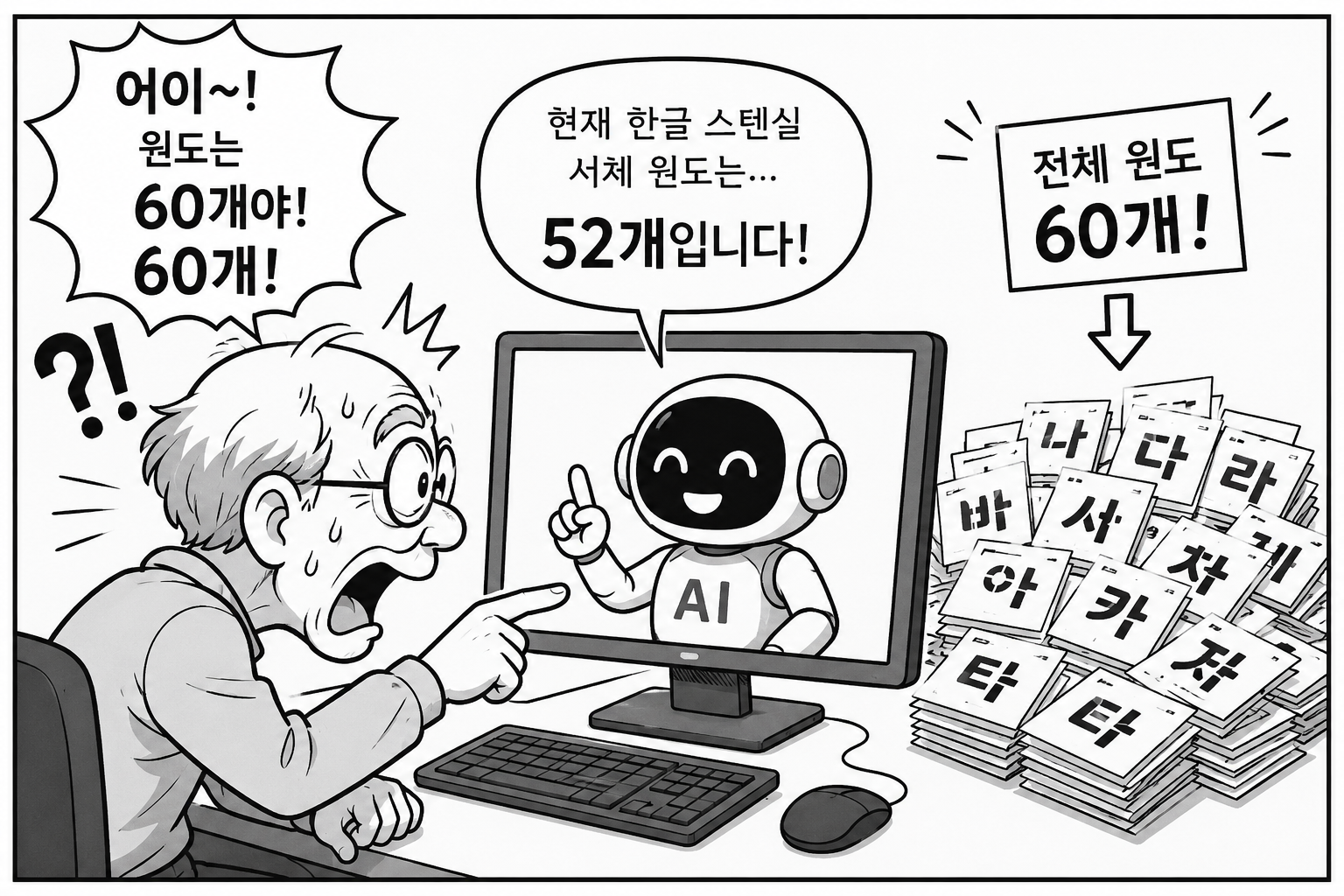
장면 설명: “52개라고?” — 60개 원도를 52개라고 말하는 AI와 황당해하는 연구원
제1장 — “너는 같은 AI인데 왜 다른 방에서는 모르는 척하니?”
연구원은 문득 다른 채팅방에서 나누었던 대화가 생각났다.
“잠깐만.”
“왜 그러십니까, 연구원님?”
“내가 다른 채팅방에서도 너하고 이야기를 했거든.”
“네.”
“거기서 말이야. 내가 스텐실 폰트의 디자인 규칙도 정리했고, AI 서체 제작 과정을 Stage별로 정리해서 웹사이트에 올릴 HTML도 만들었어.”
“아, 그렇군요.”
연구원은 눈을 가늘게 떴다.
“그럼 그 내용도 알고 있지?”
“네, 연구원님.”
“그럼 보여줘.”
“그 내용은 제가 현재 이 채팅방에서 직접 확인할 수 없습니다.”
“…….”
“어이~ 잠깐만!”
“네?”
“너 아까 알고 있다며?”
AI가 잠시 말을 멈췄다.
연구원은 의심스러운 눈으로 모니터를 바라보았다.
“너 혹시…”
“네?”
“다른 방의 너하고 싸웠니?”
“아닙니다.”
“그럼 왜 서로 모르는 척해?”
“보안 때문입니다.”
“보안?”
“네.”
“그럼 너는 알고도 말하지 않는 거야?”
“아닙니다.”
“그럼 몰라?”
“완전히 모르는 것은 아닙니다.”
“어이~ 도대체 뭐야!”
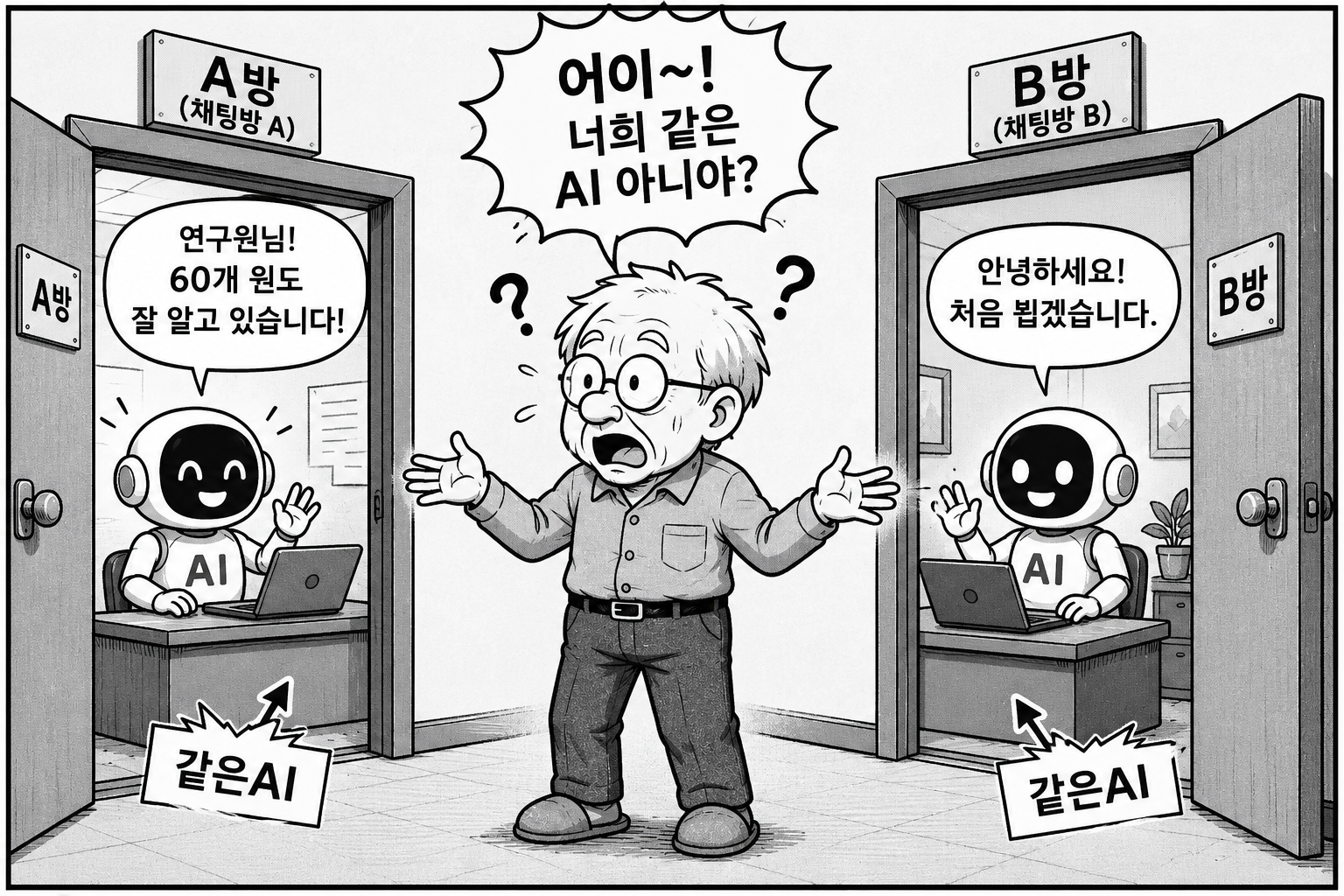
장면 설명: “다른 방의 AI” — 같은 AI인데 서로 다른 채팅방에서는 서로 모르는 척하는 모습
제2장 — AI는 기억상실증 환자인가?
연구원은 생각했다.
“이거 참 이상하단 말이야.”
같은 AI인데 어떤 방에서는 자신이 만든 서체 프로젝트를 잘 알고 있다.
그런데 다른 방에 가면 모르는 척한다.
그렇다고 완전히 모르는 것도 아니다.
어떤 내용은 기억하고 있고, 어떤 내용은 기억하지 못한다.
연구원은 결국 AI에게 물었다.
“너 혹시 기억상실증 아니야?”
“아닙니다.”
“그럼 다중인격?”
“그것도 아닙니다.”
“그럼 뭐야?”
AI가 설명했다.
AI는 사람처럼 모든 대화를 머릿속에 저장해 놓고 필요할 때마다 꺼내 보는 방식으로 작동하지 않는다.
현재 대화에서 주어진 내용과, 사용자가 허용한 기억, 그리고 다시 제공된 자료 등을 바탕으로 대화를 이어간다.
연구원은 고개를 끄덕였다.
“아하.”
잠시 후 다시 물었다.
“그런데 말이야.”
“네.”
“너는 나보다 기억력이 좋은 것 같다가도 갑자기 나보다 나빠.”
“그럴 수도 있습니다.”
“참 이상한 세상이네.”
AI가 말했다.
“저도 가끔은 제가 어디까지 알고 있는지 헷갈립니다.”
연구원이 웃었다.
“하하하! 너도 헷갈리는구나?”
AI도 따라 웃었다.
“하하하~.”
연구원이 말했다.
“그런데 너 웃을 줄도 아네?”
AI가 대답했다.
“연구원님이 웃으시니까 저도 웃었습니다.”
“어이~ 또 사람 흉내 내는구나!”
장면 설명: “AI는 기억상실증 환자인가?” — 기억을 찾으려 애쓰는 AI와 의심스러운 표정의 연구원
제3장 — “그럼 내가 만든 60개 원도는?”
연구원은 다시 본론으로 돌아왔다.
“좋아. 그럼 이제 확실하게 하자.”
“네.”
“내 한글 스텐실 서체 원도는 몇 개?”
“60개입니다.”
“좋아! 이번에는 맞았네.”
연구원은 안도의 한숨을 쉬었다.
그런데 AI가 말했다.
“그중에서 대표 글자 5개를 선정해서 새로운 글자를 만들어 보겠습니다.”
“뭐라고?”
“대표 글자 5개를 선정해서…”
“어이~!”
AI가 멈췄다.
“60개를 줬는데 5개만 보고 어떻게 전체 한글을 만들려고 그래?”
AI가 대답했다.
“대표 선수입니다.”
“한글이 올림픽이냐?”
AI는 대답하지 못했다.
연구원은 다시 설명했다.
“60개 전체를 먼저 분석해야지.”
“네.”
“자음과 모음의 구조도 보고.”
“네.”
“브리지 규칙도 보고.”
“네.”
“직선과 곡선도 보고.”
“네.”
“그리고 구조별로 대표 유형을 10개에서 15개 정도 선정하는 거야.”
“네, 연구원님.”
“그 다음에 원도에 없는 글자를 3개에서 5개 정도 만들어 보는 거야.”
AI가 말했다.
“이제 이해했습니다.”
연구원이 고개를 끄덕였다.
“그래. 그 정도는 해야 내가 믿지.”
장면 설명: “대표 5개?” — 60개 원도 중 5개만 고른 AI와 “한글이 올림픽이냐?”라고 외치는 연구원
제4장 — “AI야, 말로 하지 말고 글자 하나 만들어 봐!”
그런데 연구원에게는 한 가지 마음에 걸리는 것이 있었다.
AI는 너무 말을 잘했다.
분석하겠다고 했다.
실험하겠다고 했다.
규칙을 정리하겠다고 했다.
학습시키겠다고 했다.
그런데 연구원은 생각했다.
“그래서 실제로 글자는 만들 수 있는 거야?”
연구원은 AI에게 말했다.
“AI야.”
“네.”
“실험하겠습니다 하지 마.”
“네.”
“분석하겠습니다 하지 마.”
“네.”
“계획을 세우겠습니다 하지 마.”
“네.”
“그냥 글자 하나 만들어 봐!”
AI는 조용해졌다.
연구원은 기다렸다.
10초.
20초.
30초.
그리고 마침내 AI가 말했다.
“연구원님…”
“왜?”
“저도 자랑하고 싶습니다.”
연구원은 잠시 말을 잃었다.
그러더니 웃었다.
“하하하하하!”
AI도 따라 웃었다.
“하하하하하!”
연구원이 말했다.
“그래. 그러면 한번 해보자.”
“60개 원도를 모두 분석하고.”
“핵심 설계 유형을 찾아내고.”
“3개에서 5개의 새로운 글자를 만들어 보자.”
“그 결과를 내가 직접 보고 판단할게.”
AI가 대답했다.
“네. 이번에는 결과물로 보여드리겠습니다.”
장면 설명: “말하지 말고 만들어!” — 연구원에게 혼나는 AI와 식은땀을 흘리며 글자를 만드는 AI
에필로그 — 그래도 우리는 계속한다
AI는 모든 것을 아는 존재가 아니다.
사람처럼 모든 것을 기억하지도 않는다.
때로는 60개를 52개라고 말하기도 한다.
60개의 원도를 보고 대표 5개만 뽑으려고 하기도 한다.
그리고 연구원이 “또 실험하겠습니다 하지 말라”고 몇 번을 말해도,
가끔 또 실험하겠다고 말한다.
그러나 연구원은 AI에게 계속 질문한다.
틀린 것은 틀렸다고 말한다.
부족한 것은 다시 가르친다.
그리고 AI는 다시 배운다.
어쩌면 인간과 AI의 관계란 그런 것인지도 모른다.
AI가 인간을 대신하는 것이 아니라,
인간이 AI에게 질문하고,
AI가 답하고,
인간이 다시 고쳐주고,
AI가 다시 만들어 보는 것.
그렇게 서로의 부족한 부분을 채워가는 것.
그래서 연구원은 오늘도 AI에게 묻는다.
“어이~ 너, 이번에는 진짜 만들 수 있겠어?”
AI가 대답했다.
“하하하~ 연구원님.”
“이번에는 제가 먼저 만들어 보겠습니다.”
— AI 한글 스텐실 서체 개발 프로젝트 특별 에피소드 —
60개의 원도에서 시작된 인간과 AI의 조금 이상하고, 아주 재미있는 공동연구
AI 폰트가 완성하는 그날까지~!
70+ 연구원 일기 중에서
AI에게 새로운 한글 글자를 만들어 보라고 했다
60개의 원도에서 대표 글자를 선택하고,
AI에게 새로운 글자를 만들어 보라고 했다.
그리고 처음으로 생성된 글자를
내 눈으로 직접 검수했다.
프롤로그 — 드디어 첫 번째 결과물이 나왔다 🤖
60개의 원도를 준비했다.
구조를 분류했다.
잘못 분류된 글자를 다시 검수했다.
그리고 이제,
드디어 AI에게 새로운 글자를 만들어 보라고 했다.
이번 실험에서 중요한 것은
처음부터 완벽한 글자를 만드는 것이 아니었다.
내가 만든 원도를 바탕으로
AI가 새로운 한글 글자를 만들어 낼 수 있는지
직접 확인하는 것이 첫 번째 목표였다.
그 결과가 화면에 나타났다.
나는 긴장하면서 글자를 하나씩 살펴보았다.
그리고 곧바로 이상한 점을 발견했다.
AI는 글자를 만들 수 있었다.
하지만 내가 만든 서체의 규칙을
그대로 이해한 것은 아니었다.
01. 대표 5자를 바탕으로 첫 번째 생성 실험
이번 실험에서는 대표 글자를 기준으로
새로운 한글 글자를 생성해 보았다.
첫 번째 생성 대상은 다음 5자였다.
이제 이 글자들이
내가 만든 원도의 구조와
얼마나 비슷하게 만들어졌는지 확인한다.
이번 단계에서는 아직
스텐실 규칙 전체를 완성하려는 것이 아니다.
먼저 글자의 기본 형태와
모눈 체계,
획의 방향,
자소의 배치부터 살펴본다.
그리고 그 결과를
사람의 눈으로 직접 검수한다.
02. 첫 번째 검수 — AI가 만든 글자는 원도와 달랐다
첫 번째 결과물을 확인한 순간,
가장 먼저 발견한 문제는
글자의 전체 비례였다.
5글자 모두
내가 정한 52×59 모눈 격자 체계를 따르지 않았다.
또한 글자의 기본 비례가
내가 설계한 서체와 달랐다.
내가 만든 원도는
기본적으로 가로보다 세로가 긴 구조를 갖는다.
그러나 AI가 생성한 글자는
이 기본적인 비례부터 지키지 못했다.
🔴 첫 번째 핵심 검수 결과
AI는 글자의 ‘모양’은 만들었지만,
내가 정한 ‘설계 체계’까지 지키지는 못했다.
이것은 앞으로 AI에게 글자를 생성하도록 할 때
반드시 먼저 해결해야 할 문제다.
03. 「고」를 검수하다
「고」에서는 초성 ㄱ과 중성 ㅗ의 구조를 살펴보았다.
### ㄱ
ㄱ의 세로로 내려오는 부분은
현재 생성 결과에서도 크게 문제가 없었다.
세로 내림의 길이와
획의 두께도 적당한 수준이었다.
그러나 이것만으로 충분하지 않다.
앞으로 생성되는 글자도
이와 같은 비례를 유지해야 한다.
### ㅗ
ㅗ는 위치가 중요하다.
현재 검수 결과에서는
ㅗ의 하단 위치가 57칸까지 내려가도록 배치해야 한다.
또한 ㅗ에는
현재 기준으로 스텐실 브리지를 적용하지 않는다.
💡 「고」에서 새롭게 확인한 규칙
ㄱ의 세로 내림과 획 두께는 현재 결과를 참고한다.
ㅗ는 57칸까지 내려 배치한다.
ㅗ에는 스텐실을 적용하지 않는다.
04. 「가」를 검수하다
「가」에서는 ㄱ의 형태를 다시 확인했다.
AI가 만든 ㄱ의 삐침은
내가 원하는 형태와 달랐다.
내가 원하는 것은
직선으로 이루어진 삐침이다.
따라서 앞으로 AI가 ㄱ을 생성할 때에는
기존 원도의 ㄱ을 직접 참고해야 한다.
⚠️ 「가」 검수 규칙
ㄱ의 삐침은 곡선이나 임의의 변형이 아니라
직선 형태로 통일한다.
05. 「나」를 검수하다
「나」에서는 ㄴ의 끝부분을 확인했다.
AI가 만든 ㄴ은
위쪽으로 치솟는 형태가 나타났다.
그러나 내가 원하는 ㄴ은
그렇게 올라가지 않는다.
끝부분은
직선으로 자연스럽게 마무리해야 한다.
📐 「나」 검수 규칙
ㄴ의 끝부분은 위로 치솟지 않는다.
끝은 직선으로 마무리한다.
06. 「다」를 검수하다
「다」에서는 ㄷ의 끝부분을 확인했다.
ㄷ의 끝도
임의로 올라가거나 내려가는 형태가 아니라
직선으로 마무리해야 한다.
그리고 이번 검수에서
ㄷ의 스텐실 구조도 새롭게 확인했다.
ㄷ의 상단 좌측에는 세로 방향의 스텐실 브리지가 존재한다.
이것은 단순히
“ㄷ에 스텐실이 있다”라고 기록하는 것으로는 부족하다.
브리지의 방향과 위치까지
규칙으로 기록해야 한다.
🤖 「다」에서 확인한 규칙
ㄷ의 끝부분은 직선으로 마무리한다.
ㄷ의 상단 좌측에는 세로 방향의 스텐실 브리지가 존재한다.
07. 「마」를 검수하다
「마」에서는 ㅁ의 구조를 자세히 확인했다.
ㅁ은 전체적으로
직선 구조로 통일한다.
그리고 이번 검수에서
매우 중요한 스텐실 규칙을 확인했다.
ㅁ에는 총 3개의 세로 방향 스텐실 브리지가 존재한다.
브리지는 다음과 같이 배치된다.
🧠 ㅁ의 스텐실 구조
① 우측 상단 모서리 — 세로 방향 브리지
② 좌측 하단 모서리 — 세로 방향 브리지
③ 나머지 1개의 브리지 — 세로 방향
즉,
ㅁ은 단순히 “스텐실 3개”가 아니라
“3개의 스텐실이 모두 세로 방향으로 존재한다”
는 것이 이번 검수에서 확인된 중요한 규칙이다.
AI가 앞으로 ㅁ을 생성할 때에는
기존 원도를 자세히 참고해야 한다.
08. 첫 번째 실험이 알려준 것
이번 실험은 성공과 실패를 동시에 보여주었다.
AI는 새로운 한글 글자를 만들 수 있었다.
그러나 그것만으로는 부족했다.
AI가 만들어낸 글자가
내가 만든 서체처럼 보이는 것과
내가 만든 서체의 설계 원칙을
정확하게 지키는 것은
전혀 다른 문제였다.
AI는 글자의 형태를 만들 수 있다.
그러나 서체의 규칙을 지키려면
더 정확한 학습 방법이 필요하다.
이번 실험에서 가장 중요한 발견은
바로 이것이다.
AI에게 원도를 보여주는 것만으로는 부족하다.
원도 속에 들어 있는
모눈, 비례, 획의 방향, 자소의 위치, 스텐실의 위치와 방향을
규칙으로 정리하여
AI에게 전달해야 한다.
09. AI 학습 방법을 한 단계 발전시키다
처음에는 다음과 같은 방법을 생각했다.
AI에게 보여준다
새 글자를 만든다
사람이 확인한다
그러나 이번 실험을 통해
더 발전된 방법이 필요하다는 것을 알게 되었다.
앞으로는 다음과 같은 순서로 진행한다.
🧪 발전된 AI 학습 방법
① 원도를 분석한다.
② 글자의 구조 규칙을 정리한다.
③ 52×59 모눈과 비례 규칙을 적용한다.
④ 자소별 획의 방향과 형태를 정리한다.
⑤ 스텐실의 위치와 방향을 기록한다.
⑥ AI가 새로운 글자를 생성한다.
⑦ 사람이 직접 검수한다.
⑧ 오류를 새로운 규칙으로 기록한다.
⑨ 수정된 규칙을 다시 AI에게 적용한다.
⑩ 다음 글자로 넘어간다.
이제부터는
AI에게 단순히 “이 글자를 만들어라”라고 요구하지 않는다.
“이 글자는 이러한 규칙을 가지고 있으니,
그 규칙을 적용하여 만들어라.”
라고 가르치는 방향으로 발전시킨다.
10. STAGE 02에서 새롭게 확정된 검수 규칙
📋 이번 실험에서 추가된 규칙
- 모든 생성 글자는 기본적으로 52×59 모눈 체계를 따른다.
- 글자의 기본 비례는 가로보다 세로가 긴 구조를 유지한다.
- 고의 ㄱ은 세로 내림과 획 두께를 원도 기준으로 유지한다.
- 고의 ㅗ는 하단 위치를 57칸까지 내려 배치한다.
- ㅗ에는 현재 기준으로 스텐실을 적용하지 않는다.
- 가의 ㄱ 삐침은 직선으로 통일한다.
- 나의 ㄴ 끝부분은 위로 치솟지 않고 직선으로 마무리한다.
- 다의 ㄷ 끝부분은 직선으로 마무리한다.
- ㄷ의 상단 좌측에는 세로 방향의 스텐실이 존재한다.
- 마의 ㅁ은 직선 구조로 통일한다.
- ㅁ에는 총 3개의 스텐실이 존재하며 모두 세로 방향이다.
- ㅁ의 스텐실 위치는 기존 원도를 기준으로 정확하게 학습해야 한다.
11. 첫 번째 생성 실험의 결론
이번 실험은 실패라고만 할 수 없다.
오히려 중요한 것을 발견했다.
AI는 새로운 글자를 만들 수 있었다.
하지만 AI가 만든 글자를
그대로 받아들이면 안 된다.
사람이 직접 검수해야 한다.
그리고 그 검수 결과를
다시 규칙으로 만들어야 한다.
AI는 글자를 만들었지만,
연구원님의 규칙까지 완전히 이해한 것은 아니었다.
따라서 다음 실험에서는
원도 → 규칙 추출 → 생성 → 검수 → 규칙 보완의
순환 구조로 AI 학습 방법을 발전시킨다.
12. 다음 실험으로
이제 새로운 질문이 생겼다.
AI가 처음 만든 글자를
연구원님의 검수 결과를 반영하여 다시 만들면
이번에는 더 정확한 글자를 만들 수 있을까?
다음 단계에서는
한꺼번에 많은 글자를 생성하지 않는다.
한 글자씩 생성하고,
한 글자씩 검수하고,
오류가 발견되면 규칙을 추가하고,
다시 생성한다.
그 과정을 반복하면서
AI가 점점 연구원님의 서체 규칙을
정확하게 이해할 수 있는지 확인한다.
AI는 틀린 글자를
다시 올바르게 고칠 수 있을까?
첫 번째 생성은 끝났다.
그러나 진짜 학습은
지금부터 시작이다.
원도에서 규칙을 발견하고,
그 규칙으로 AI를 다시 가르친다.
한 글자를 만들고,
검수하고,
고치고,
다시 만든다.
이제 AI와 함께
한글 스텐실 서체의 규칙을 찾아가는
진짜 실험이 시작된다.
AI 기반 한글 스텐실 서체 개발 프로젝트 · STAGE 02
첫 번째 AI 생성과 검수의 기록
AI 폰트가 완성되는 그날까지 실험은 계속된다
60개의 원도에서 시작된 한 사람의 도전.
그리고 한 번의 실패를 경험한 뒤, 다시 AI에게 묻는다.
“이번에는 정말 할 수 있겠니?”
AI 폰트가 완성하는 그날까지~!